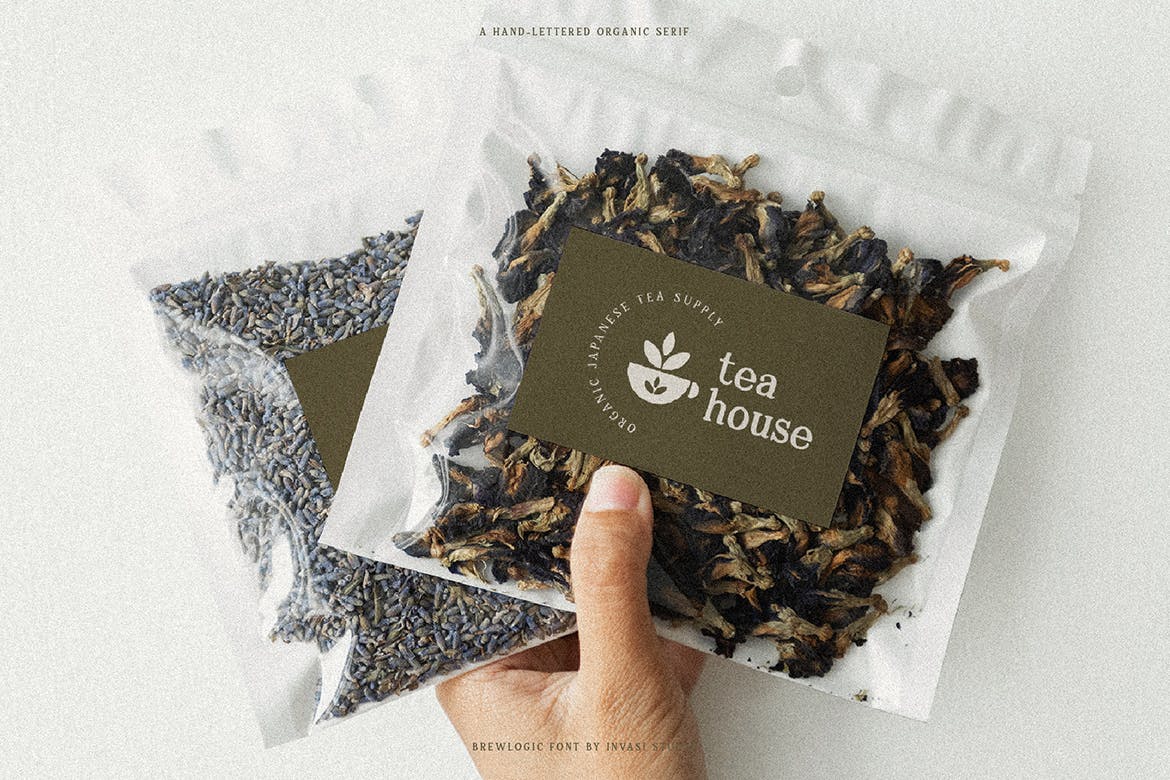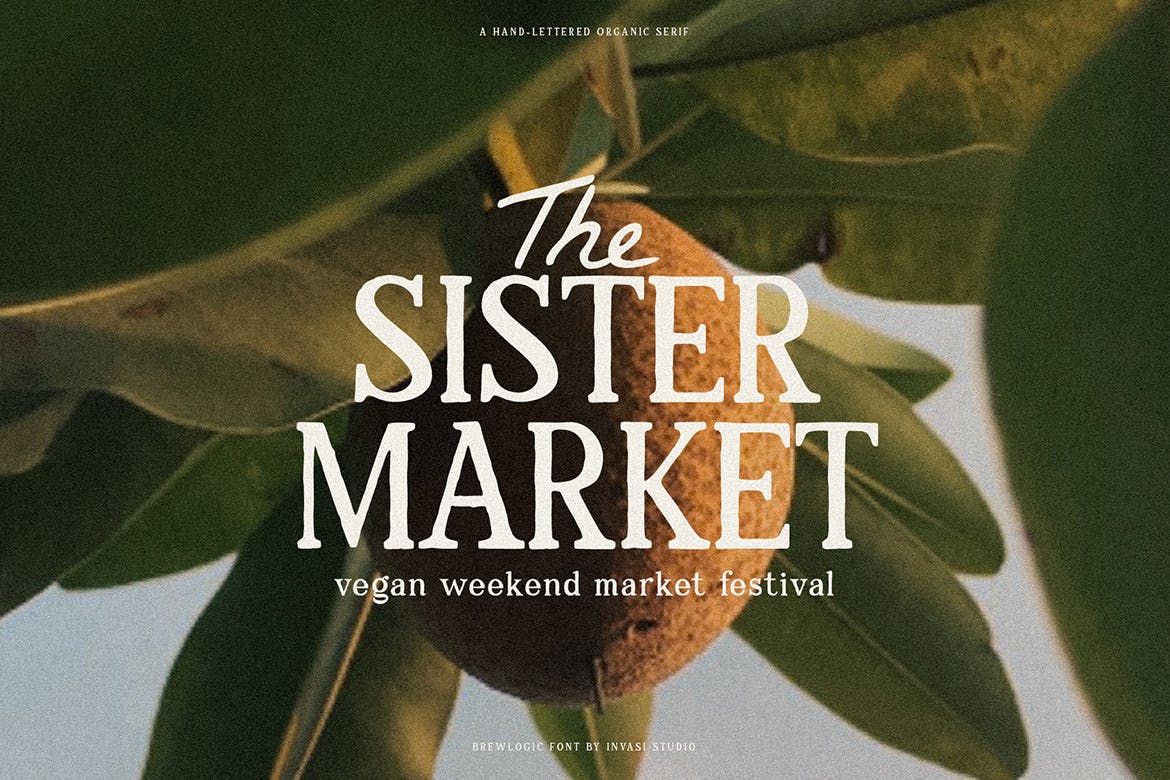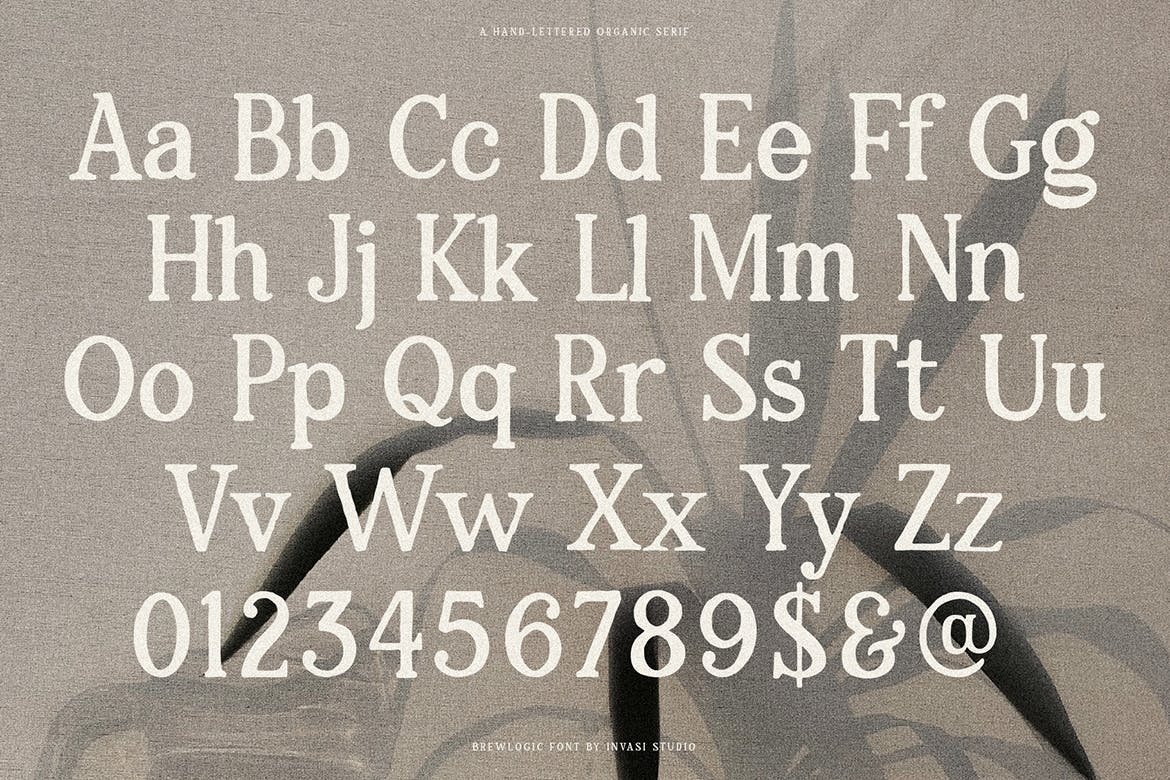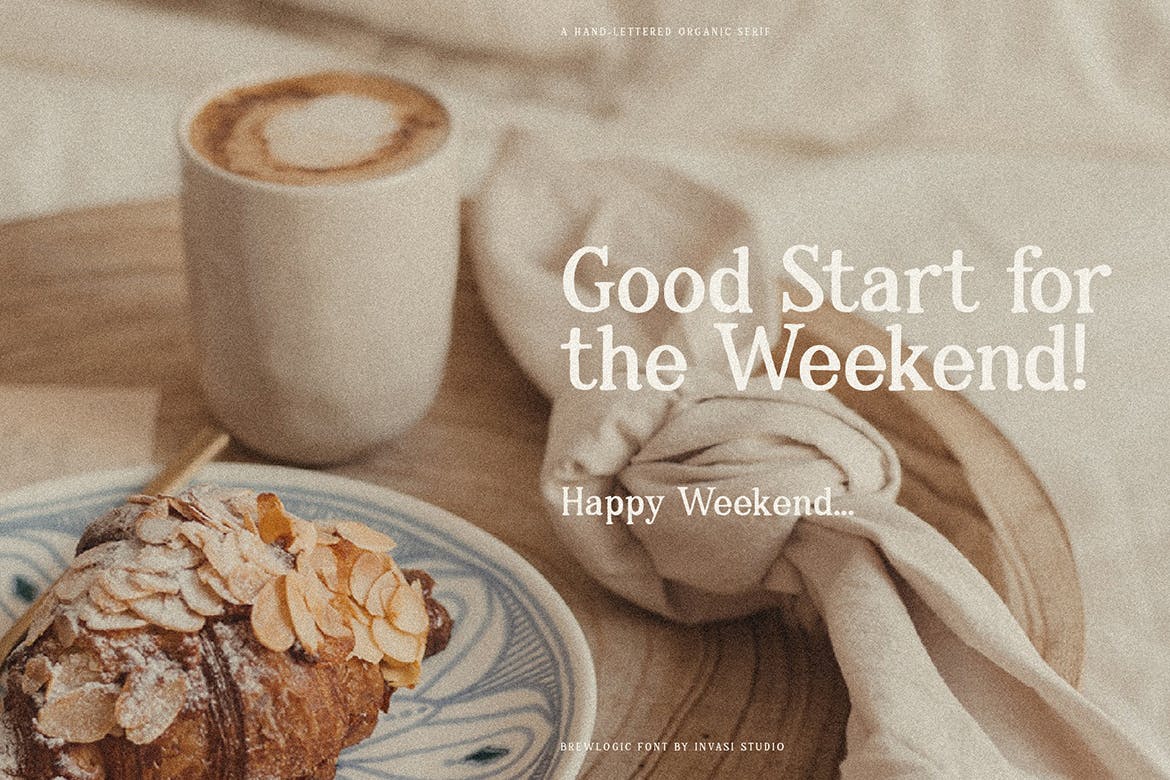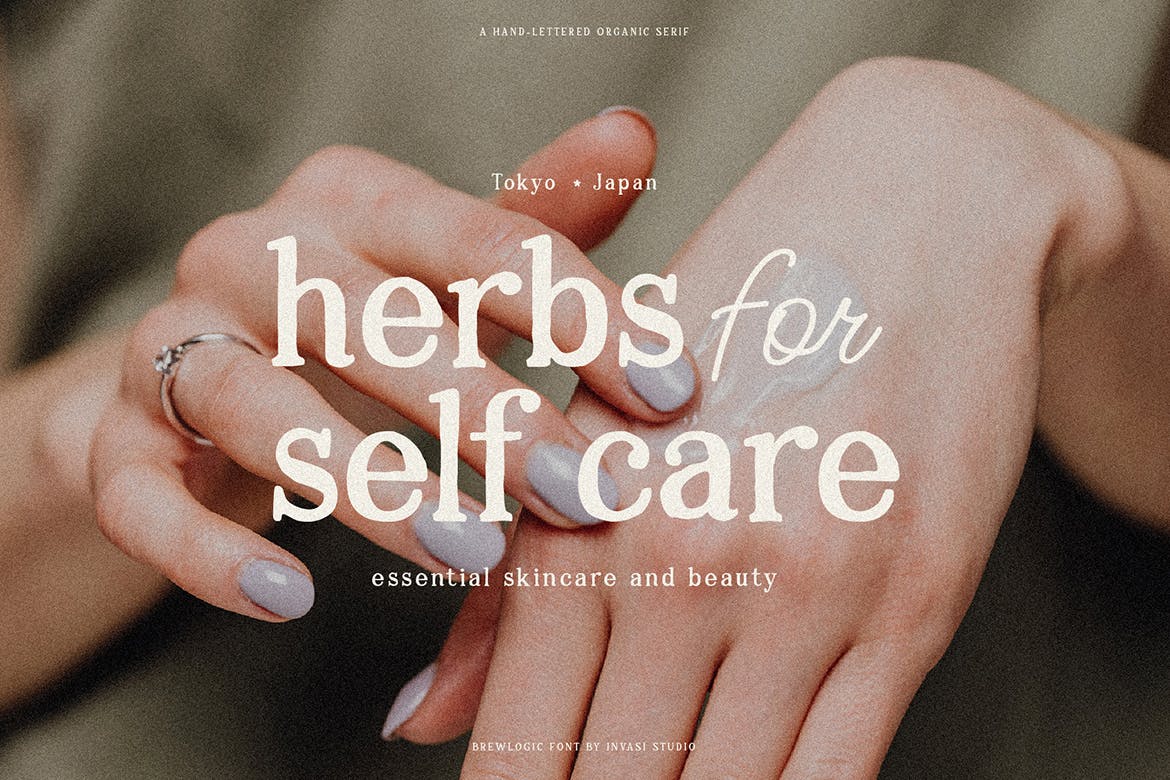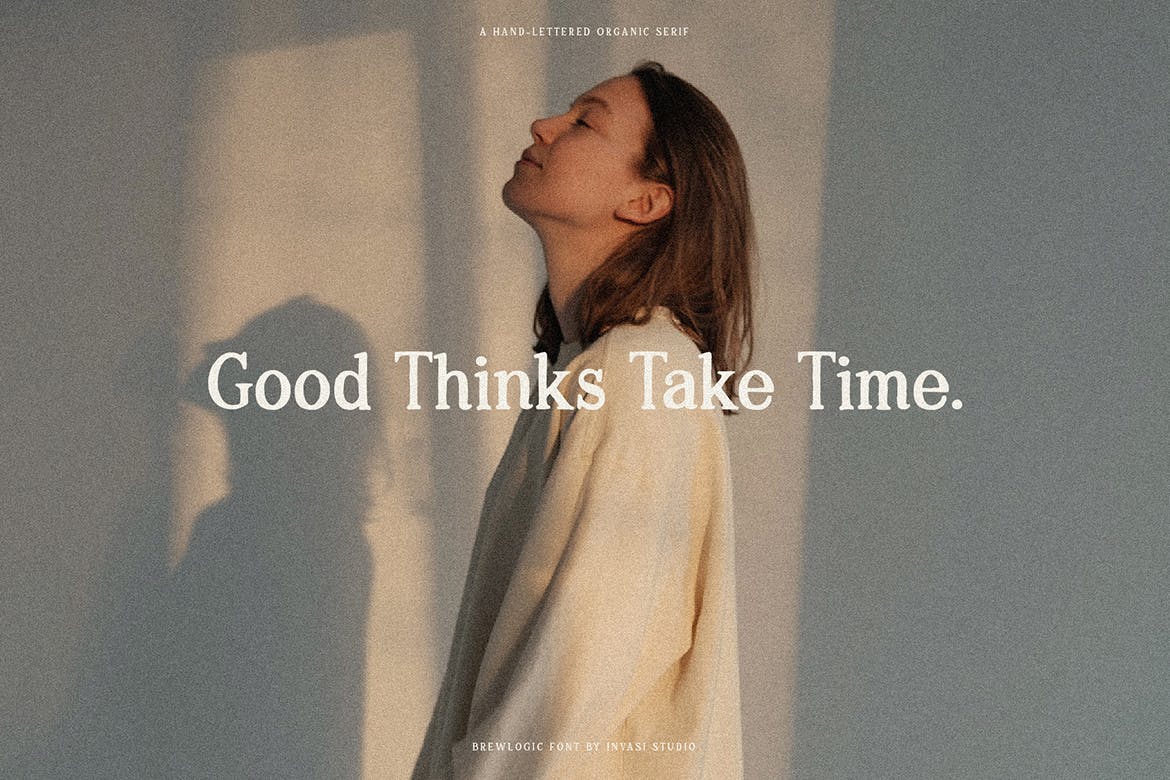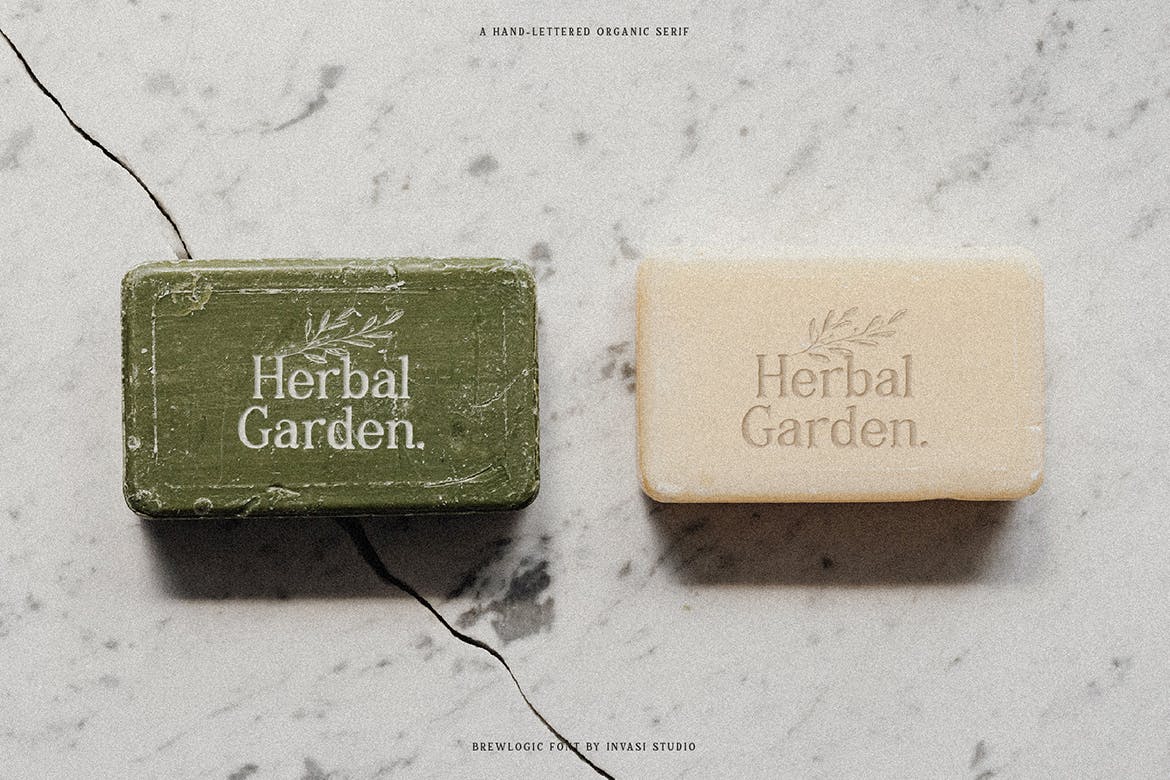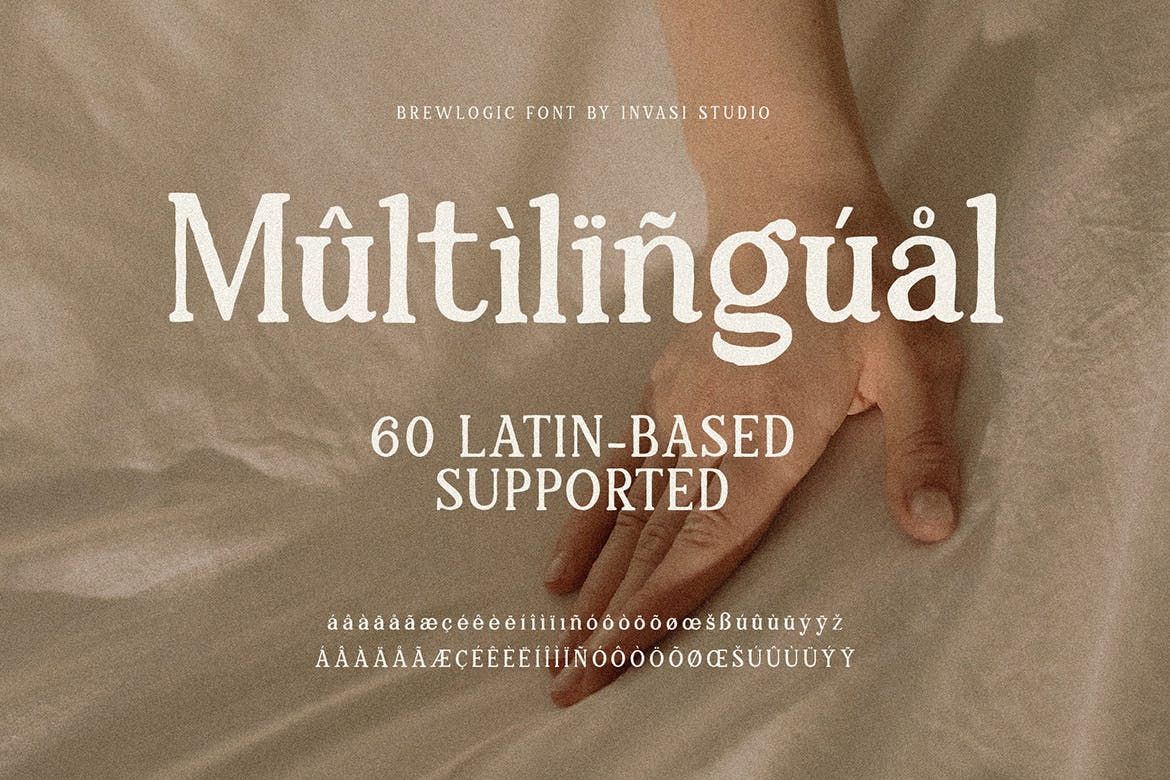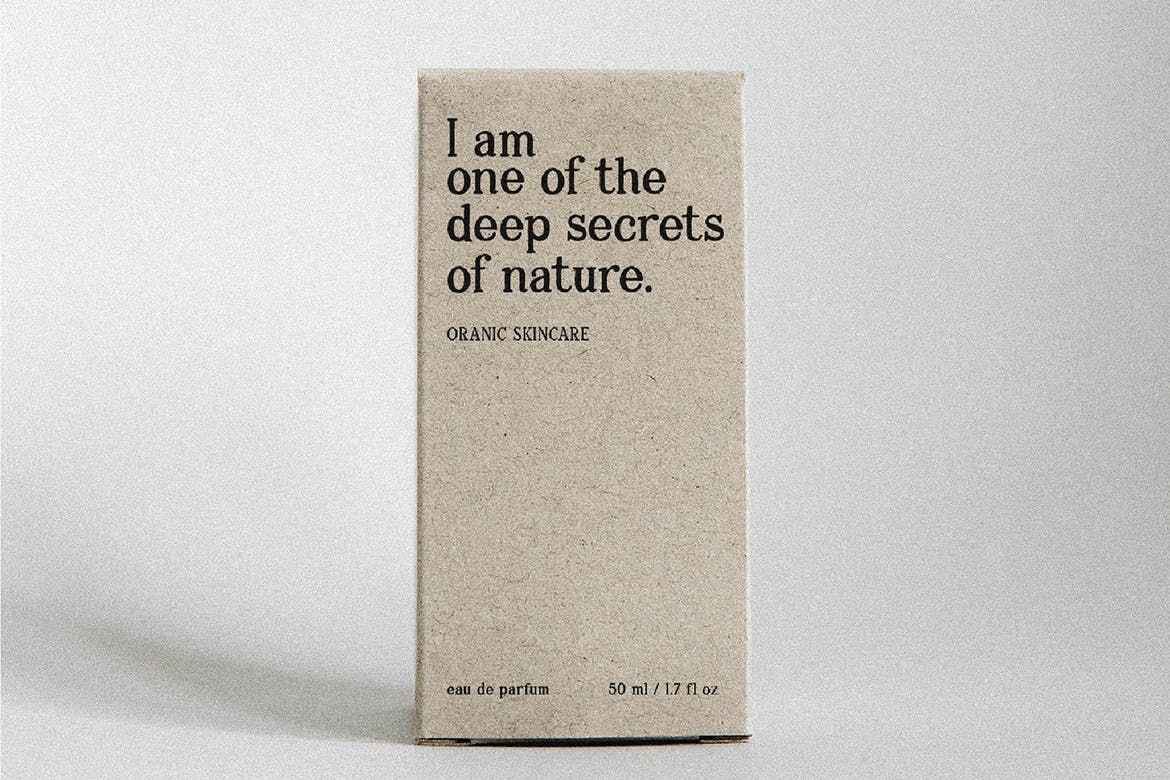
Brewlogic Organic Display Font
فنجان قهوه‌تان را بردارید و از فونت نمایشی ارگانیک ما لذت ببرید! Brewlogic یک فونت سریف دست‌نویس است که به زیبایی با طراحی‌های جدید شما هماهنگ می‌شود.
بهترین راه برای نمایش سلیقه عالی شما، استفاده از این فونت در برچسب‌ها و بسته‌بندی‌هاست. فونت‌های نمایشی ارگانیک ما به خوبی با سبک و لحن برند شما سازگار هستند!
ویژگی‌ها:
• 292 گلیف در مجموع
• حروف بزرگ و کوچک
• اعداد و نشانه‌گذاری
• پشتیبانی از 60+ زبان مبتنی بر لاتین
• لیگاتورها